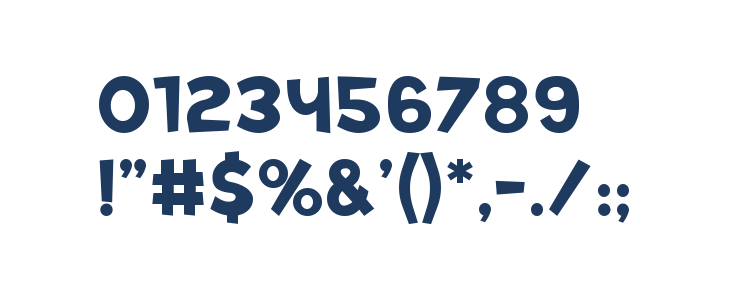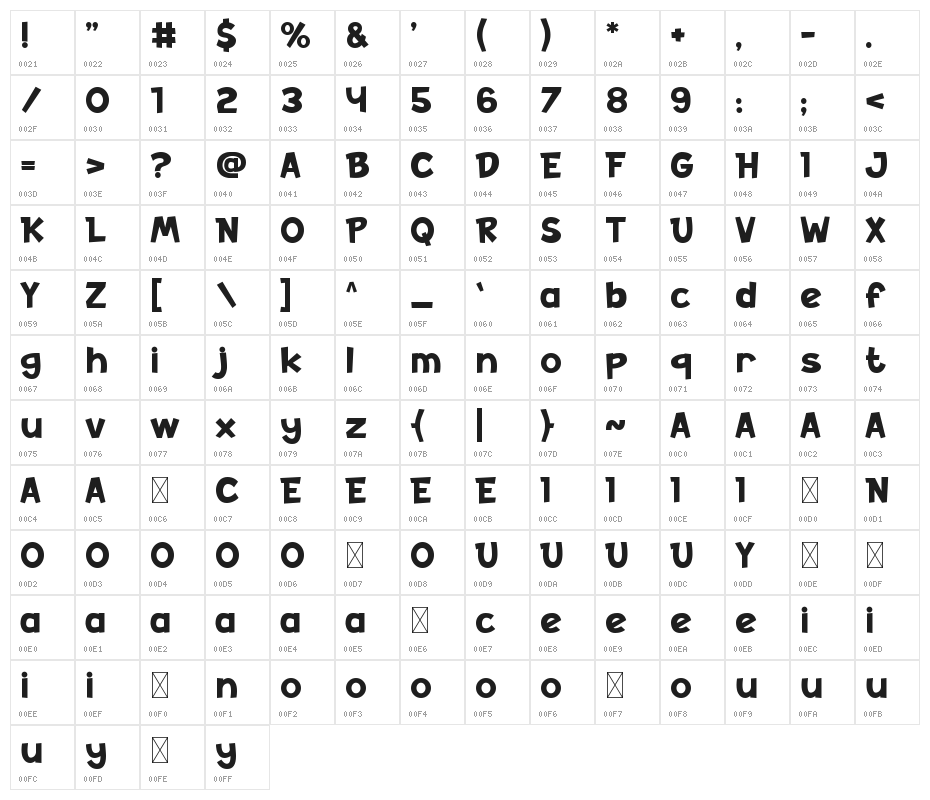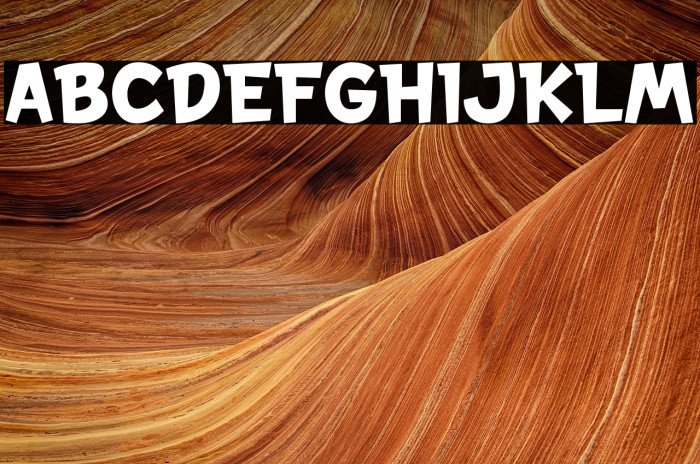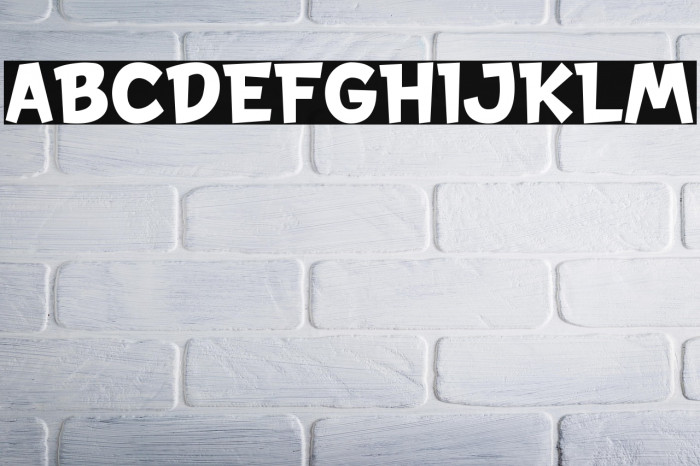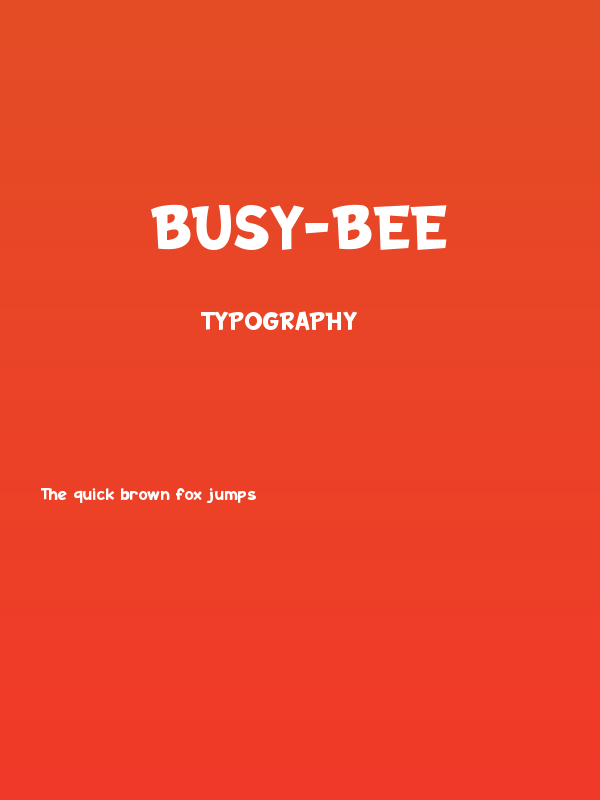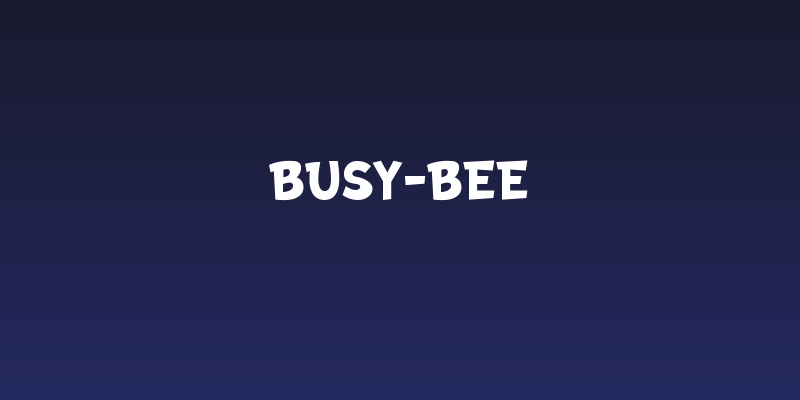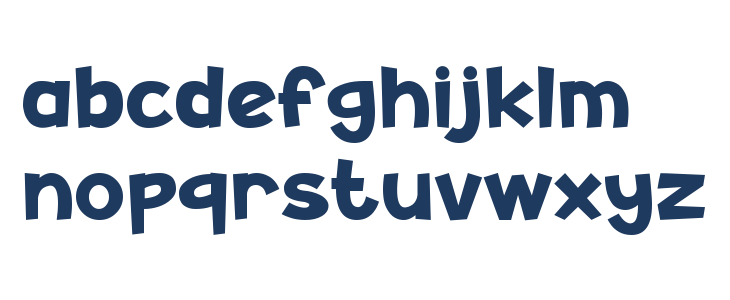
Busy-Bee Font
| Stile generale | Playful, Cartoon-like |
| Progetti proposti | Ideal for children's books, comic strips, playful branding, and party invitations. |